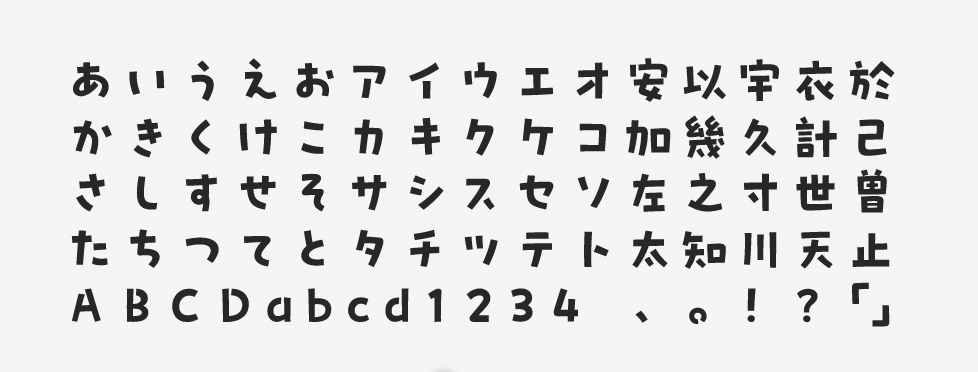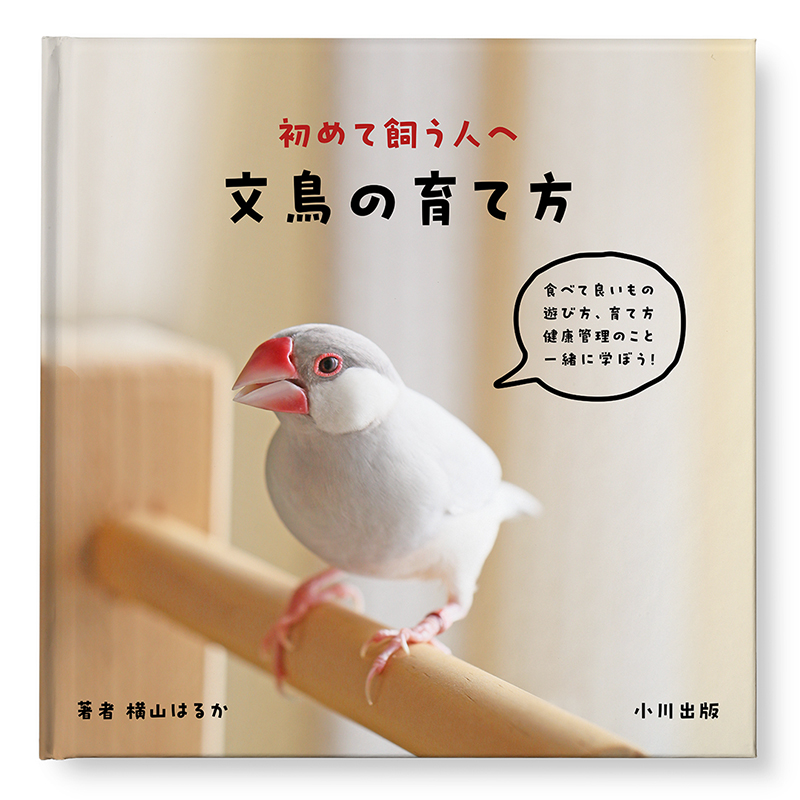
「プフ ポッケ」について
統一しすぎない自由な字形や小さめの字面を特徴とする「プフシリーズ」のフォントの1つで、2022年にリリースされました。同シリーズにはこのほかにも、プフ ホリデー、プフ マーチ、プフ ピクニックといったバリエーションがあります。プフ ポッケは、ゴシック体風のデザインをベースにしたフォントです。
「プフ ポッケ」の特徴
「プフシリーズ」は楽しくて可愛いフォント群です。プフ ポッケは、ゴシック体をベースとしつつも、上側の折り返し部分がカーブ状になっています。このカーブは、フォントの開発時には「なで肩」と呼ばれていたそうです。元気さと同時に、力が入りすぎていないイメージを表現しやすいでしょう。
なお、本フォントには「プフシリーズ」に特有の “隠し要素” もあります。独自のキャラクター絵文字が1つ収録されており、異体字としての選択入力が可能です。
ゴシック体というよりは、太めの手描き系フォントとしてイメージすると扱いやすいかもしれません。太めのペンでゆっくり丁寧に書いているような印象もあります。カーブ具合が可愛いので、力強いというイメージはほぼありませんが、シンプルさは感じるフォントです。